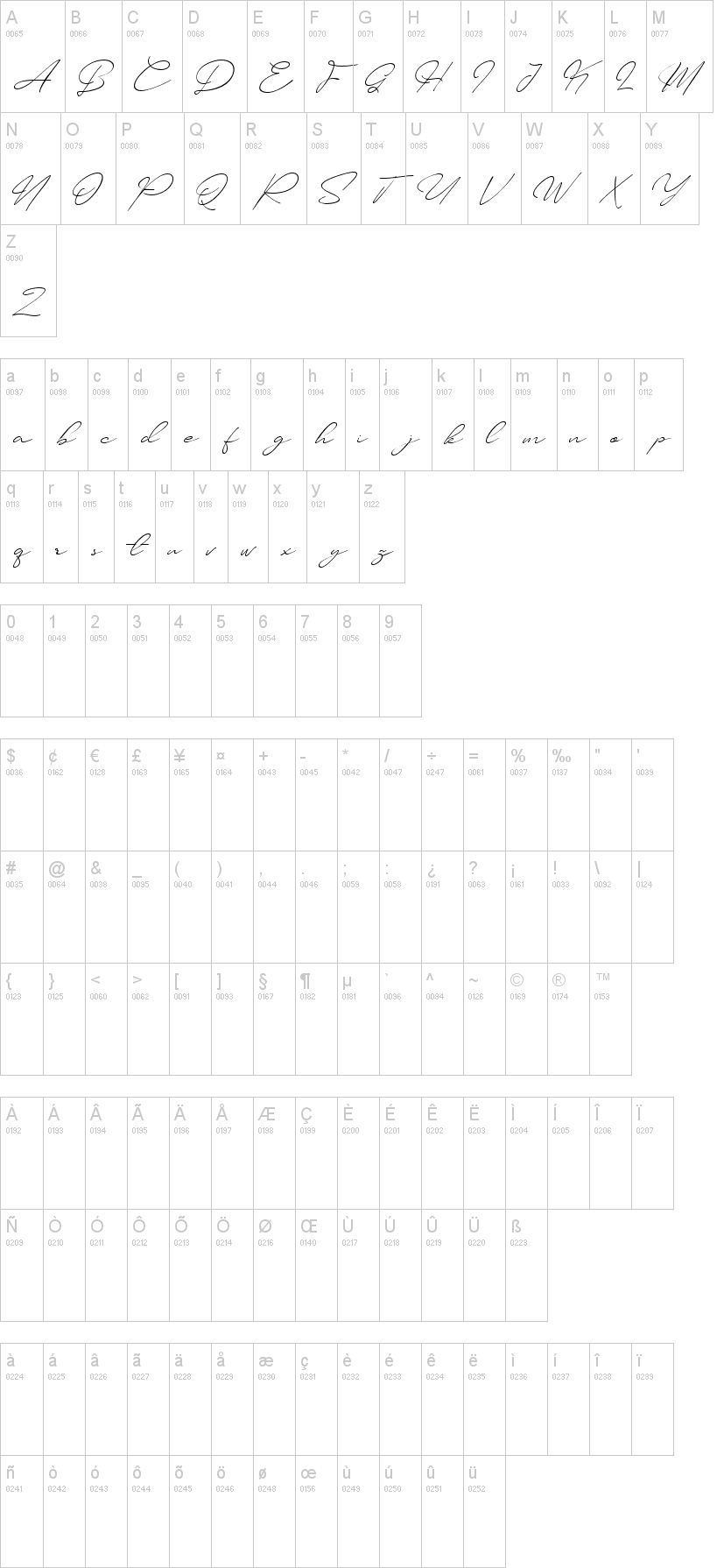
Hello Santuy是一款简洁优雅的字体,由英国设计师Cristina Pagnotta设计。它的每一个字母都简洁明快,没有多余的装饰,表达出了一种简洁而又不失优雅的感觉。它可以用于制作各种类型的海报、标志、标语等,也可以用于网站、印刷品、广告等。内容介绍
Hello Santuy是一款非常不错的手写艺术字体,具有很好的视觉感,适合于文化类的宣传设计、商业类品牌的广告和产品包装设计以及个性化文字排版等较多场景。